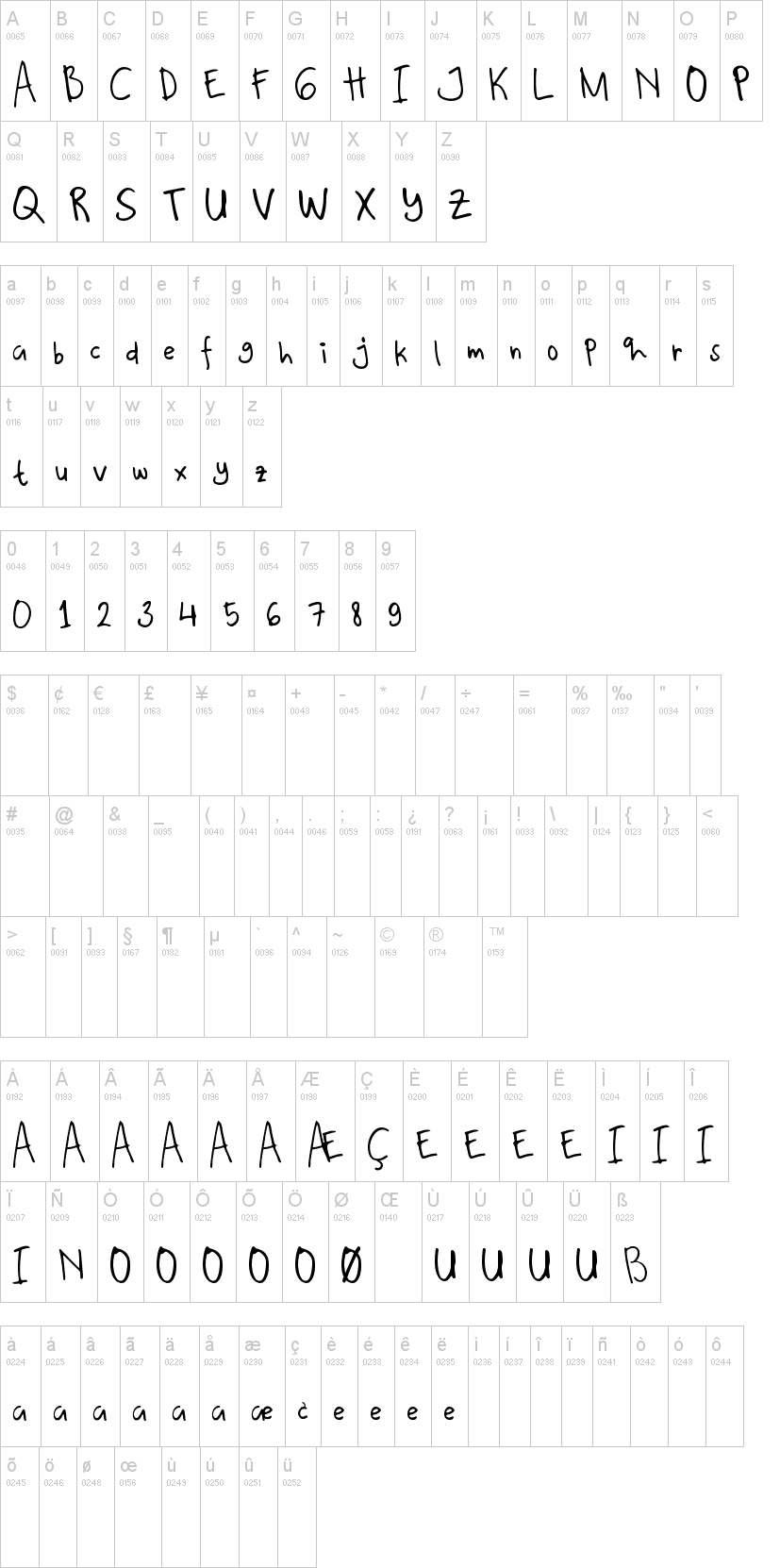
Kalyana 字体是一款多语言支持的漂亮字体,它被设计用来支持文字的多种语言,包括英语、泰语、印地语、马来语、越南语和印度尼西亚语。Kalyana 字体的特点是它的字体细节非常精细,能够更好地表达字体的丰富性和多样性。Kalyana 字体的文字特征也非常完善,能够支持多种语言,比如英文、泰文、印地文、马来文、越南文和印度尼西亚文。Kalyana 字体的字体特征也很丰富,能够支持多种字体风格,比如楷书、行书、草书和篆书。内容介绍
Kalyana是一款非常不错的手写艺术字体,具有很好的视觉感,适合于文化类的宣传设计、商业类品牌的广告和产品包装设计以及个性化文字排版等较多场景。